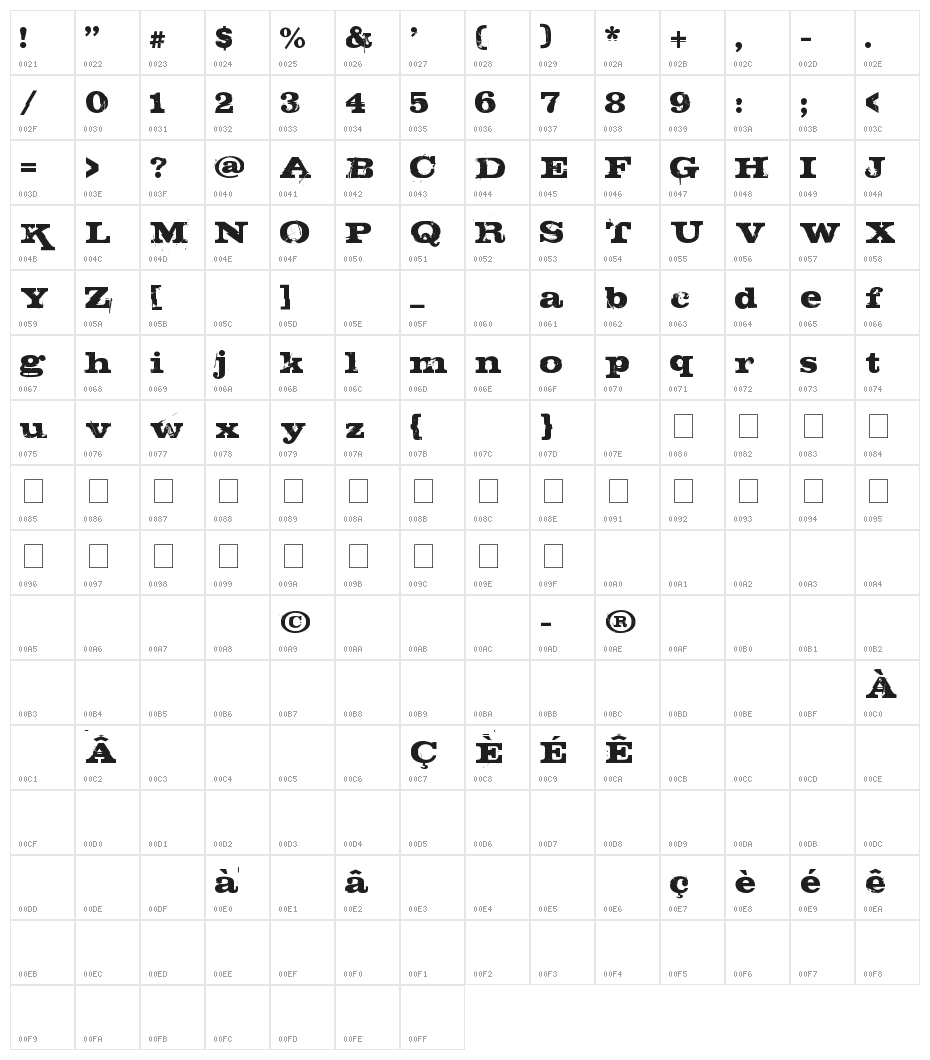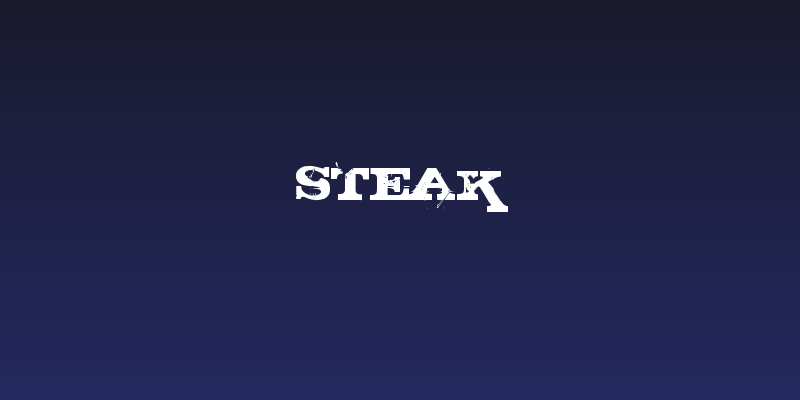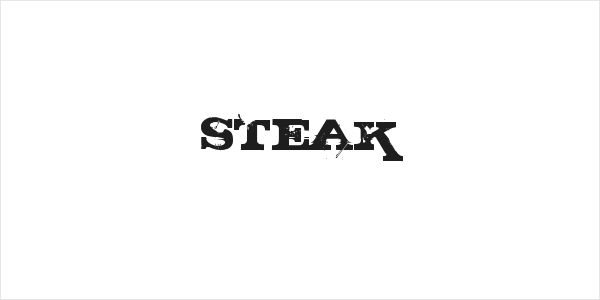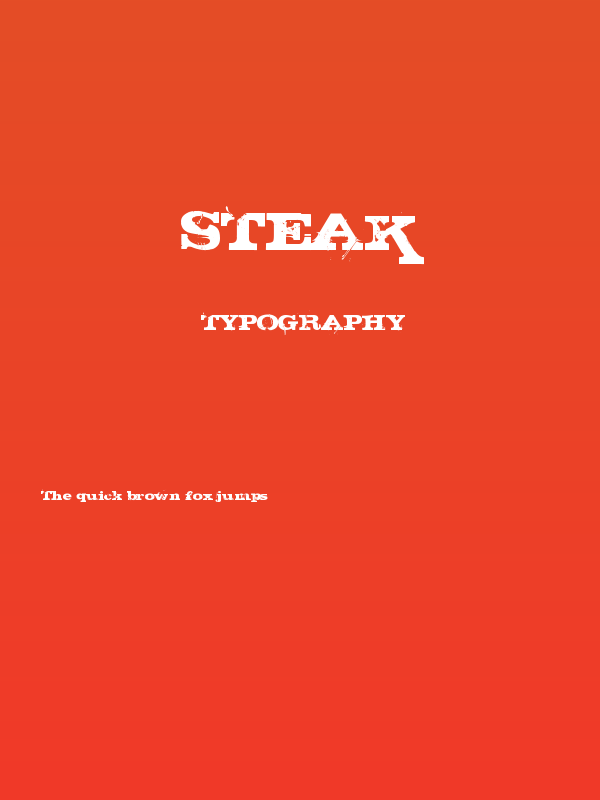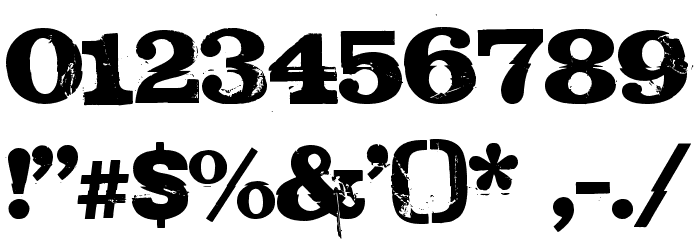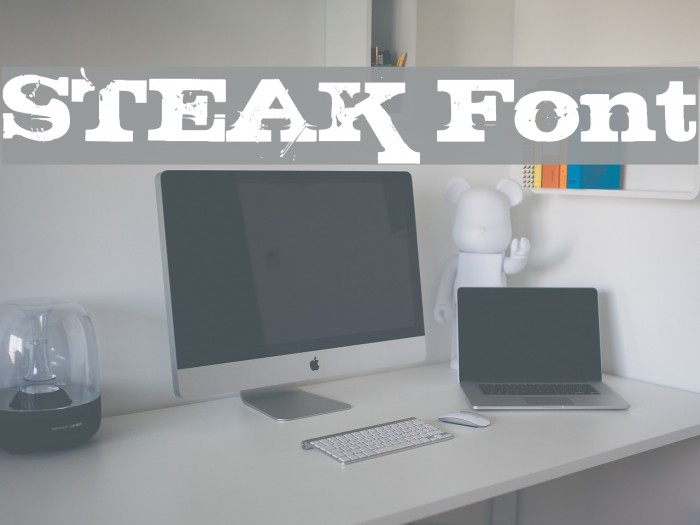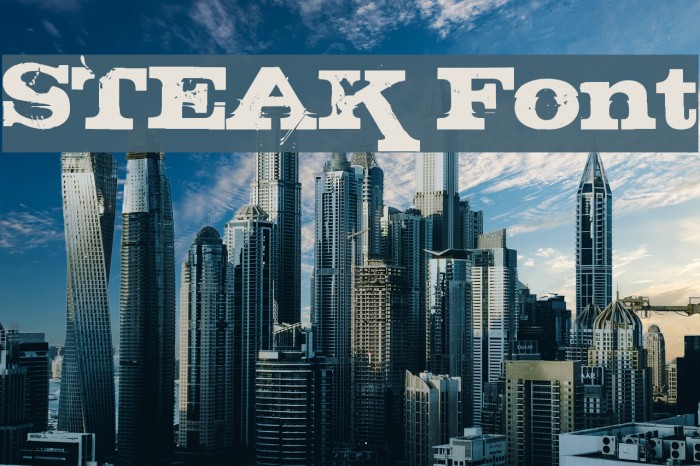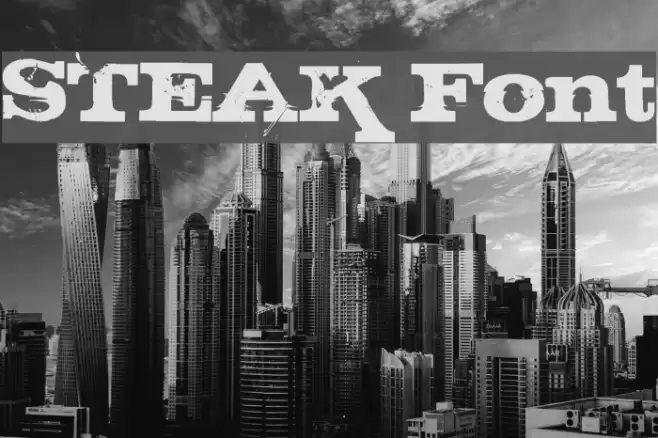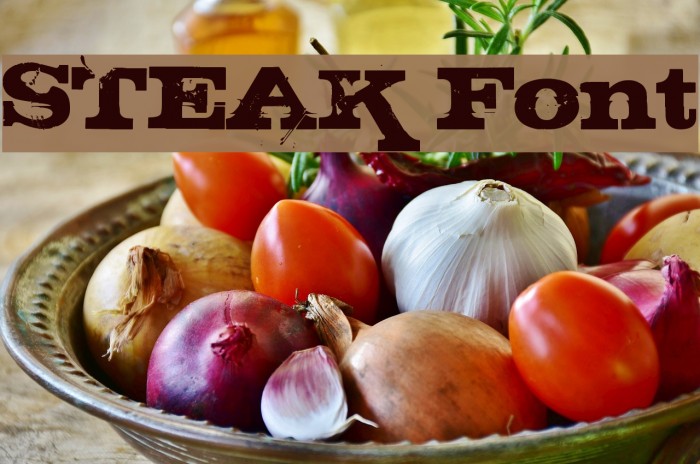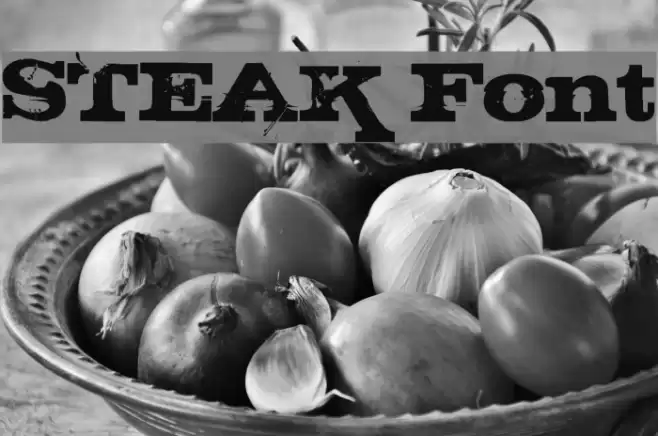
STEAK Font
✎ Distorted Eroded
| श्रेणियाँ | Distorted Eroded |
| समग्र शैली | Vintage |
| उपयोग का मामला | Headlines, Logos, Posters |
| सुझाए गए प्रोजेक्ट | Perfect for vintage posters, album covers, branding for rugged products, or any design needing a bold, distressed look. |